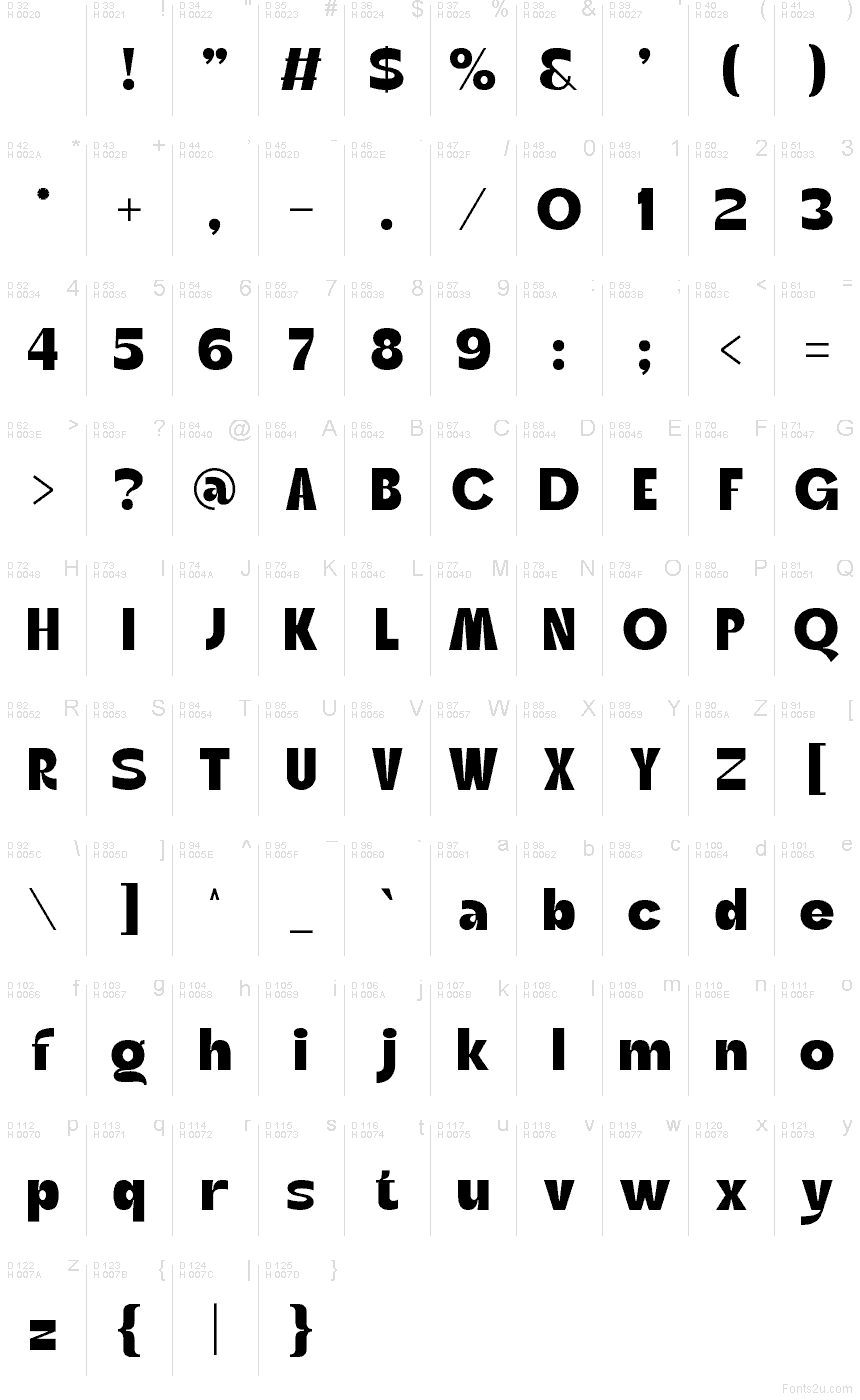
Aglea
Aglea, realizzata da Ermedia Studio, è un font display moderno e gratuito che combina forme imponenti dal taglio netto con curve morbide e generose. Il disegno delle lettere alterna verticali monumentali a forme circolari ampie, mentre le curve ben definite conferiscono al design un ritmo editoriale espressivo.
Questo font gratuito è ideale per testate di moda, poster culturali, copertine di riviste e sistemi di identità visiva. Funziona particolarmente bene in titoli brevi e scritte di impatto, dove il contrasto tra la rigidità delle verticali e la fluidità delle curve riesce a emergere senza sovraccaricare la composizione.